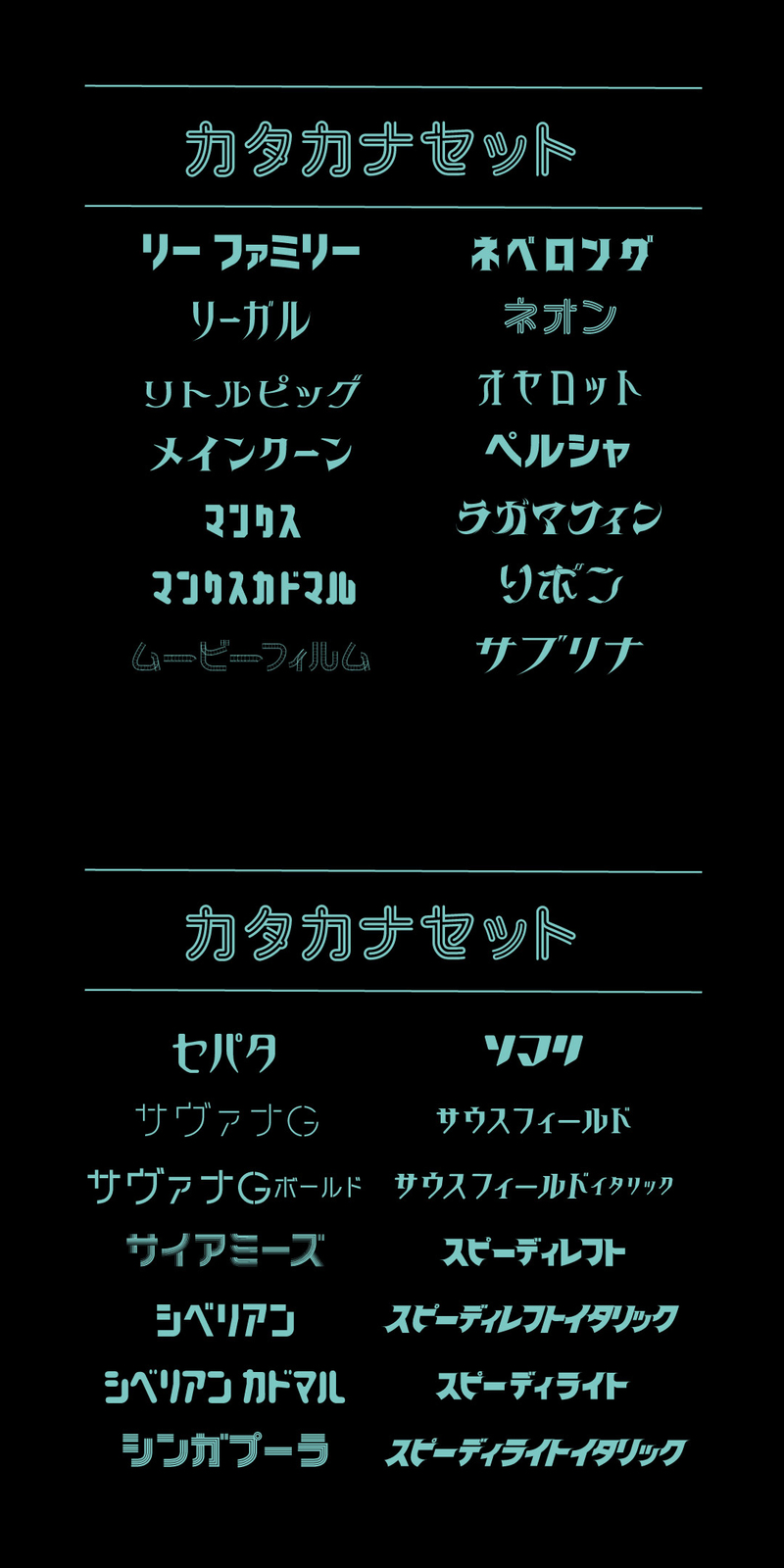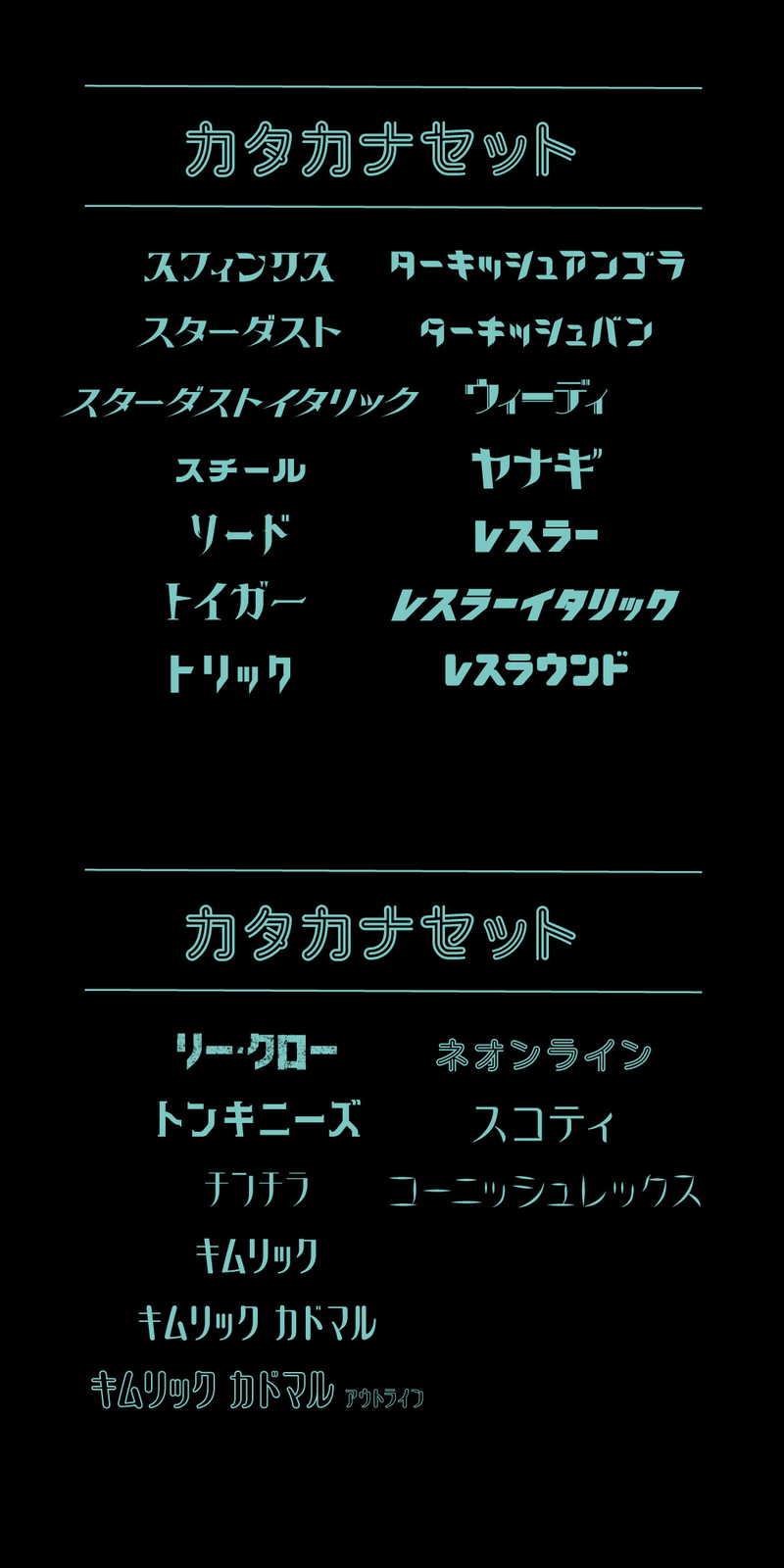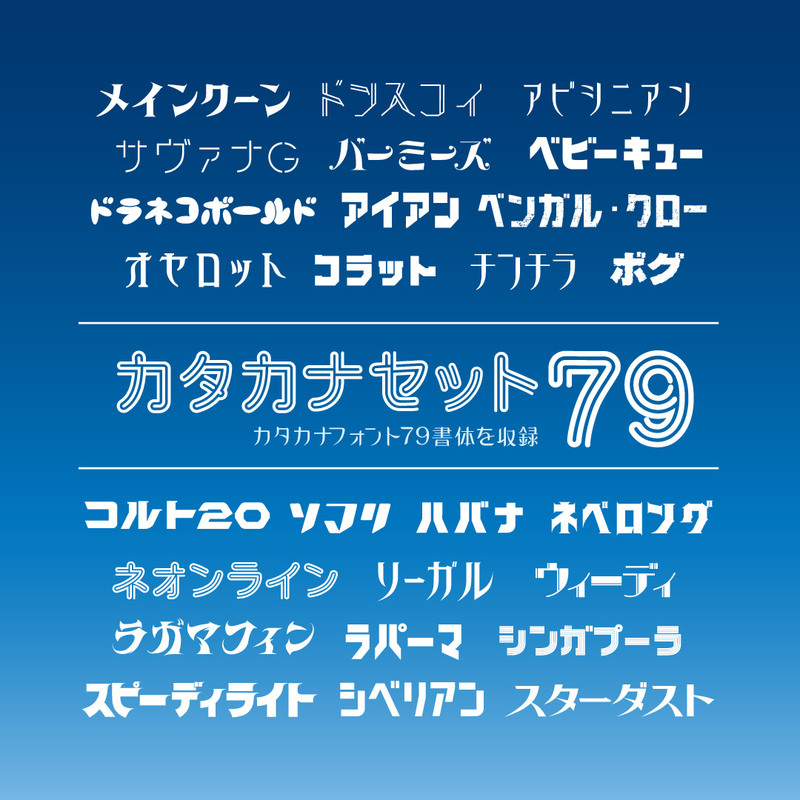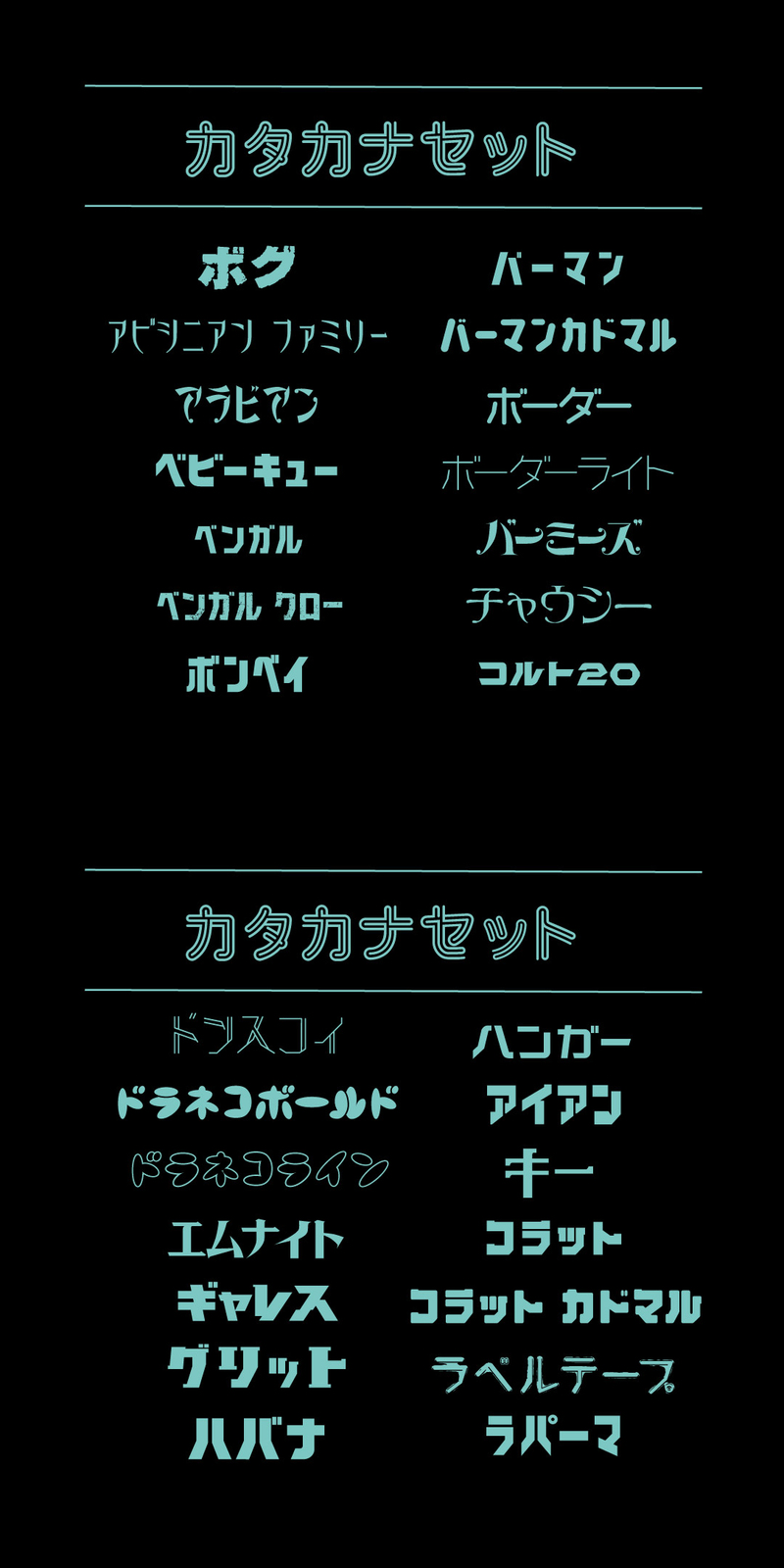
商用利用可能なオリジナルフォントです。カタカナのみ・Open Type・2バイト。
Chiba Designでリリースしたバラエティ豊かなカタカナフォント79書体。ポスター、フライヤーなどの印刷物、webバナーなど広告物、ロゴデザインなどにお使いいただけます。
本商品は下記79書体のセットです。
アビシニアン ファミリー 、アラビアン 、ベビーキュー 、ベンガル 、ベンガル・クロー 、バーマン 、バーマン カドマル、ボンベイ 、ボーダー、ボーダーライト 、バーミーズ 、チャウシー 、コルト20 、ドンスコイ 、ドラネコ ライン 、ドラネコ ボールド 、エムナイト 、ギャレス 、グリット 、ハバナ 、ハンガー 、アイアン 、キー 、ラベルテープ 、ラパーマ 、リー ファミリー 、リーガル 、リトルピッグ 、メインクーン 、マンクス カドマル 、マンクス 、ムービーフィルム 、ネオン 、オセロット 、ペルシャ 、ラガマフィン 、リボン 、サブリナ 、サヴァナGボールド 、サヴァナG 、セパタ 、サイアミーズ 、シベリアン 、シベリアン カドマル 、シンガプーラ 、ソマリ 、サウスフィールド 、サウスフィールド イタリック 、スピーディレフト 、スピーディレフト イタリック 、スピーディライト 、スピーディライト イタリック、スフィンクス 、スターダスト 、スターダスト イタリック 、スチール 、ソード 、トイガー 、トリック 、ターキッシュアンゴラ 、ターキッシュバン 、ウィーディ 、ヤナギ 、レスラー 、レスラー イタリック 、レスラウンド 、リー・クロー、トンキニーズ、コラット、コラットカドマル、チンチラ、キムリック、キムリック カドマル、キムリック カドマル アウトライン、ネオンライン、ネベロング、ボグ、スコティ、コーニッシュレックス
※一部書体はひらがな、アルファベットも含まれます。
※プレビューフォントは「サブリナ」です。